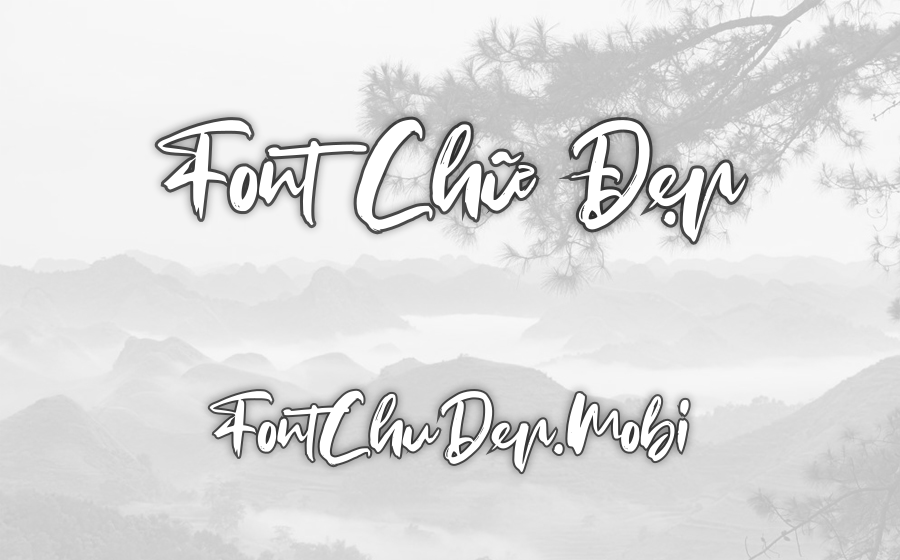
Font LNTH Wintersoul Việt Hóa
LNTH Wintersoul
Font Wintersoul mang đến một trải nghiệm nghệ thuật thư pháp đầy cảm xúc, dễ dàng chiếm trọn trái tim của những ai yêu thích phong cách lãng mạn và tinh tế. Với những nét chữ uốn lượn mềm mại, linh hoạt, font chữ này thực sự là một tác phẩm nghệ thuật tuyệt vời cho các dự án sáng tạo, đặc biệt trong những thiết kế lấy cảm hứng từ mùa đông, Giáng sinh hay bất kỳ sự kiện cá nhân nào.
Phiên bản Font Wintersoul đã được LNTH chăm chút để hỗ trợ tốt tiếng Việt cũng như hơn 50 ngôn ngữ khác, điều này mở ra nhiều cơ hội ứng dụng trong các thiết kế quốc tế. Nguồn cảm hứng từ thư pháp hiện đại đã làm cho Wintersoul trở thành lựa chọn lý tưởng cho những ai đang tìm kiếm sự mềm mại và lãng mạn trong thiết kế, được cộng đồng FontChuDep.mobi đặc biệt yêu thích và chia sẻ.
Đặc trưng nổi bật của Font Wintersoul chính là những nét chữ uyển chuyển, độ dày mỏng thay đổi một cách tự nhiên, phản ánh sự tinh tế và thanh thoát như những nét chữ viết tay. Đây chắc chắn là một lựa chọn hoàn hảo cho typography nghệ thuật, thư mời, thiệp cưới, logo thiết kế thượng hạng, và những sản phẩm thủ công cao cấp.
Ứng dụng của Font Wintersoul rất đa dạng, từ các dịp lễ hội như Giáng sinh, Valentine đến thiệp cưới và nhiều sự kiện lãng mạn khác. Dù ở bất kỳ ngành nghề nào, từ quảng cáo, thiết kế thương hiệu cho đến spa hay trang trí sự kiện, Wintersoul vẫn thể hiện được sức hút và sự phù hợp ấn tượng của mình.